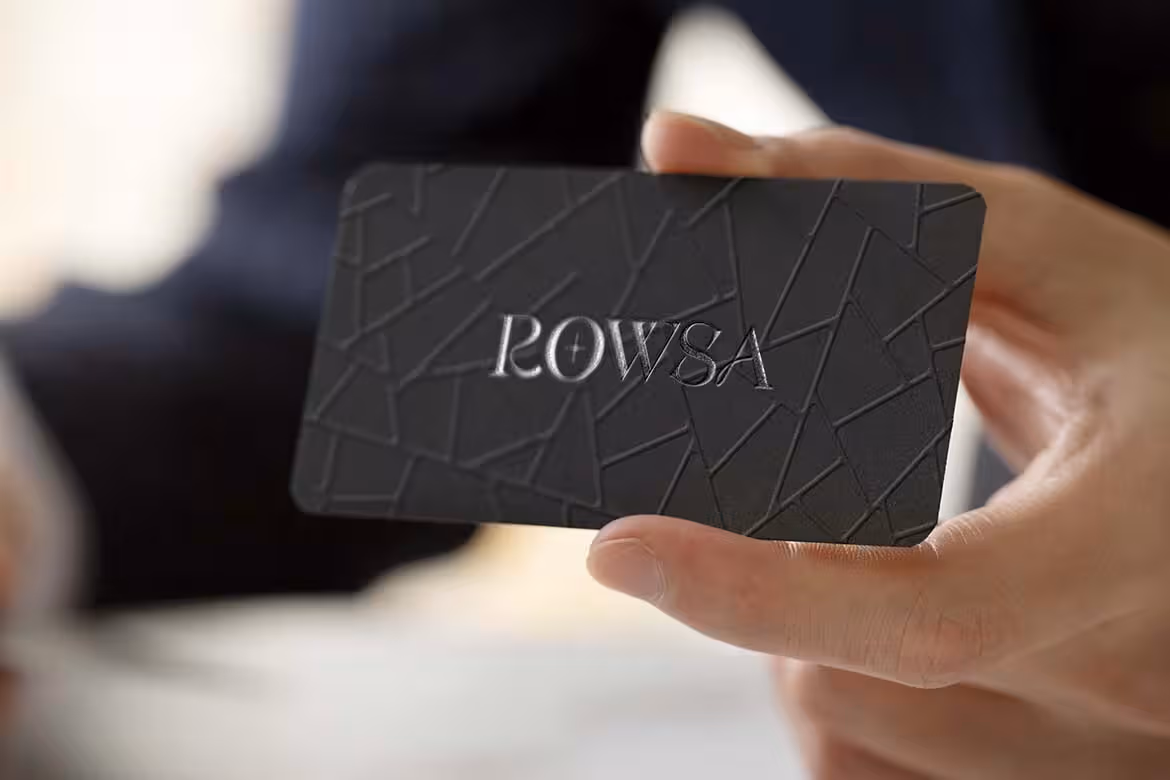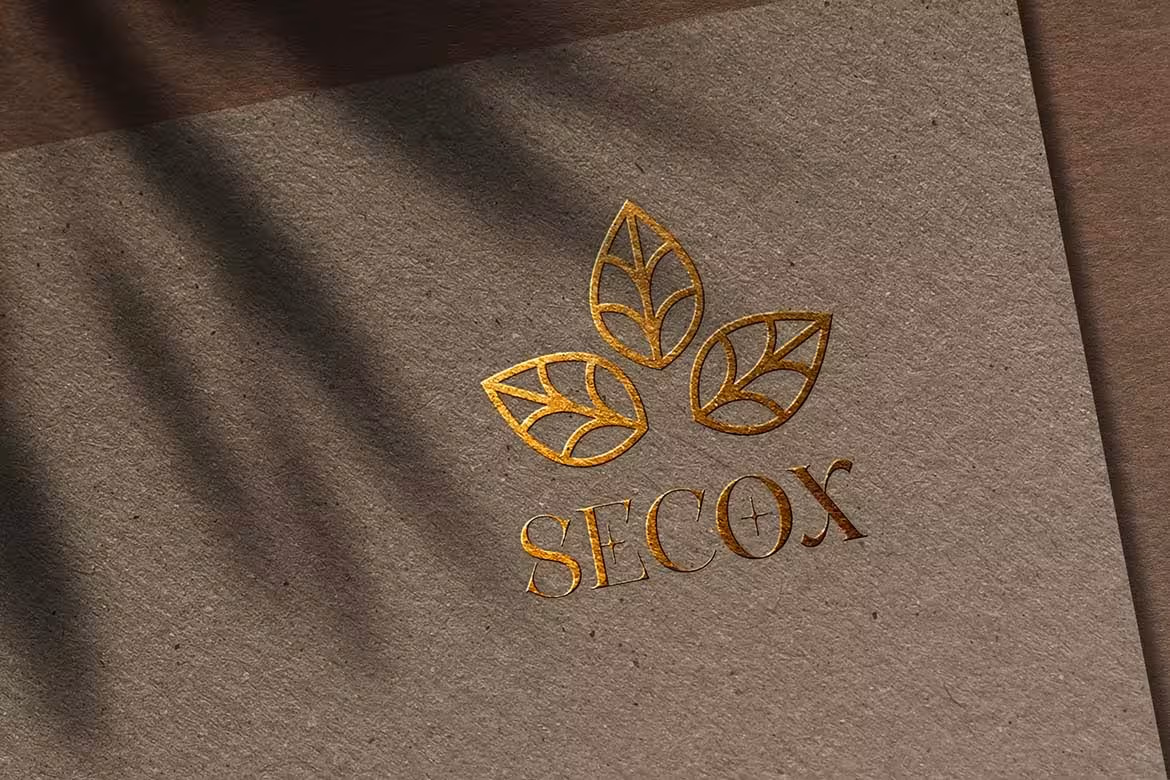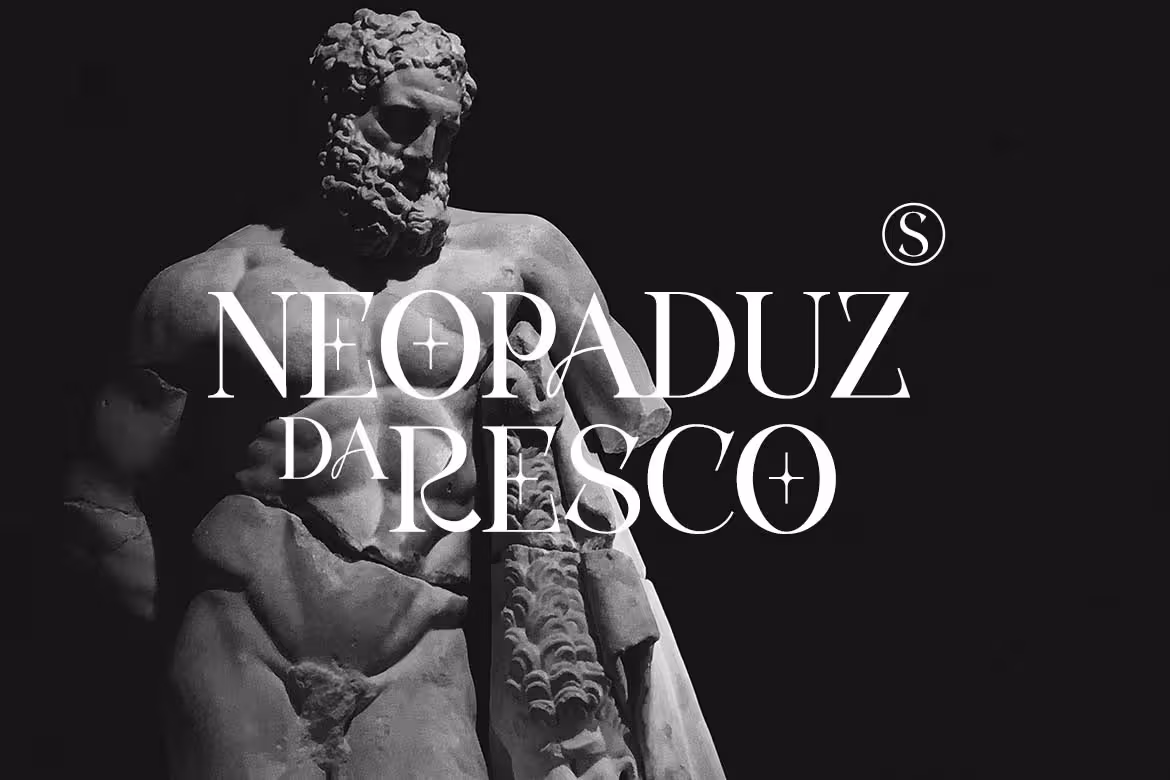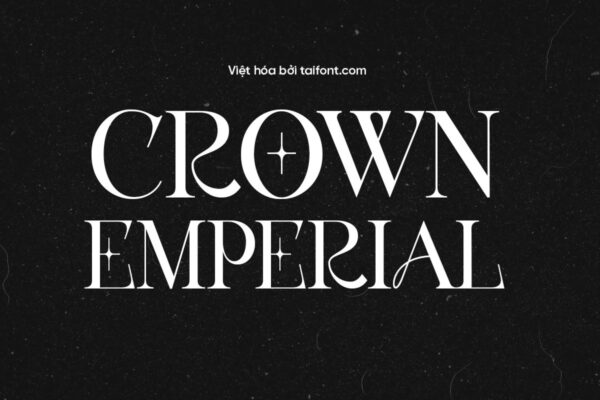
Giới thiệu về Font TF Crown Imperial Việt hóa
TF Crown Imperial Việt hóa là một font chữ có chân (serif) được mệnh danh là đỉnh cao của vẻ đẹp và sự tinh tế. Với những đường nét được thiết kế vô cùng sang trọng, uyển chuyển và đầy quý phái, font này toát lên sự đẳng cấp vượt trội, mang đến cảm giác vương giả và thanh lịch.
TF Crown Imperial là lựa chọn hoàn hảo cho các thiết kế đòi hỏi sự xa hoa, độc quyền và phong thái hoàng gia, bao gồm:
- Thiết kế thiệp: Tuyệt vời cho thiệp mời sự kiện cao cấp, tiệc gala, lễ kỷ niệm hoặc các buổi lễ mang tính trang trọng, giúp mỗi tấm thiệp trở thành một tác phẩm nghệ thuật.
- Bưu phẩm sang quý phái: Phù hợp cho các ấn phẩm như giấy tiêu đề, bì thư, hoặc các tài liệu mang tính chất ngoại giao, khẳng định đẳng cấp của người gửi.
- Thiết kế thương hiệu xa xỉ: Lý tưởng cho logo và bộ nhận diện của các thương hiệu thời trang cao cấp, trang sức, đồng hồ, hoặc các dịch vụ thượng lưu.
- Ấn phẩm mang tính nghệ thuật, lịch sử: Thích hợp cho các dự án cần tái hiện vẻ đẹp cổ điển, hoàng gia hoặc những giá trị vượt thời gian.
Với TF Crown Imperial Việt hóa, bạn có thể dễ dàng tạo ra những thiết kế không chỉ đẹp mắt mà còn truyền tải được sự sang trọng, quý phái và đẳng cấp, làm nổi bật giá trị của từng chi tiết.
Font Việt hóa TF Crown Emperial – Font cho MV ca nhạc